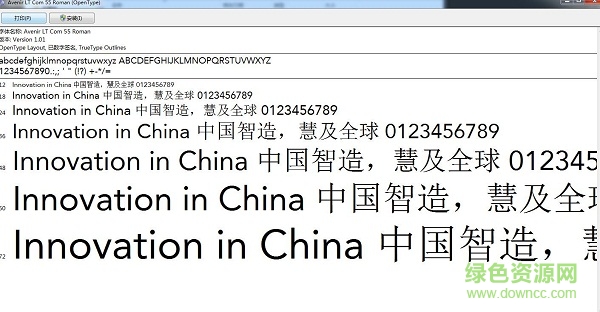
軟件介紹 軟件標(biāo)簽: avenir字體 英文字體 avenirltcom medium字體是一款粗細(xì)勻稱的英文無襯線字體,字體線條流暢干凈,氣質(zhì)理性非常實用,需要更多英文廣告字體的朋友快來綠色資源網(wǎng)免費下載吧!avenir字體推薦avenir book英文字體 授權(quán):免費軟件 WinAll, WinXP, Win7大小:571KB語言:中文avenirbook字體是一款西文字體,該字體沒有襯線裝飾,筆畫纖細(xì),字形簡約干練,極具韻致,需要的小伙伴快來綠色資源網(wǎng)下載!字體安裝方法方法一:控制面板/字體/文件/安裝新字體;方法二:直接將字體復(fù)制到C:\WI下載地址 avenirnext regular字體 授權(quán):免費軟件 WinAll, WinXP, Win7大?。?00KB語言:中文avenirnextregular字體是一款可以在photoshop和Word等軟件中使用的英文字體,該字體的筆劃粗細(xì)大小都非常得當(dāng),印刷效果清晰,文章報刊、平面設(shè)計都可以,歡迎大家免費下載!字體設(shè)計的個性要求1.在設(shè)計時要避免與下載地址外文字體分類外文字體的種類較多,常用的有白正體、黑正體、白斜體、黑斜體、花體等。白體一般用于書刊的正文,黑體用于標(biāo)題。avenirltcom字體安裝方法1.需要進(jìn)行字體安裝方可調(diào)用字體2.將字體拖動到C:\Windows\Fonts文件夾進(jìn)行安裝3.如若編輯器內(nèi)未顯示字體文件,可重新打開編輯器查看 軟件截圖 上一張下一張(1 / 1) 安裝詳細(xì)截圖 其他版本下載 標(biāo)題 大小 更新日期 下載 下載地址 電腦版 avenirltcom medium 點擊報錯 軟件無法下載或下載后無法使用,請點擊報錯,謝謝! 關(guān)閉報錯反饋 請描述您所遇到的錯誤,我們將盡快予以修正,謝謝! *必填項,請輸入內(nèi)容 本類最新 sounso beauty字體 spyced哥特英文字體 ttf版 zerodegrees字體 the next font ttf版 coolvetica font keep calm ttf 免費版 相關(guān)文章 我叫mt4哪個職業(yè)輸出最高 我叫mt4輸出最高的職業(yè)排行 用CMailServer打造郵件服務(wù)器 空白密碼引發(fā)遠(yuǎn)程連接Server2008失敗 Linux(CentOS)服務(wù)器/VPS上安裝DirectAdmin linux系統(tǒng)SendMail詳細(xì)配置 SMTP安全手冊—Sendmail服務(wù)器安全 用戶評論 熱門評論 最新評論 發(fā)表評論 查看所有評論(0) 昵稱: 請不要評論無意義或臟話,我們所有評論會有人工審核. 字?jǐn)?shù): 0/500 (您的評論需要經(jīng)過審核才能顯示)